手機如何換字體?怎麼做到的?
過去一段時間,偶而會看到身旁人的手機,使用了極其特殊的字體,那種與一般常見作業系統預設黑體大相逕挺的風格,令人過目難忘。
濫觴:手機的普及化
在大約2000年初,智慧型手機逐漸嶄露頭角,但當時還是以類似「黑莓機」的形式出場,往往帶著一個實體鍵盤,直到2000年末,賈伯斯帶的第一代iPhone問世,各家廠商紛紛跟進「全觸控」的手機市場。
在硬體的加持下,我們開始可以將較為複雜的運算功能移植到行動端上,智慧型手機也愈發普及,從原本簡單的「商務使用」到「人手一機」。
資本家的嗅覺:Monotype 進軍手機字體市場
使用的人多了,就有商機,此時世界上最大的字體帝國Monotype嗅到商機,希望可以開發一款能「換字體」的工具,當時在2007到2010年之間,手機製造商如雨後春筍般冒出,包括:Nokia、Samsung、Apple等,作業系統部分,也是各立門戶,不像現在只有Android與iOS。
最早Monotype其實是為Nokia的Symbian作業系統打造換字體技術。Monotype將此技術稱為「FlipFont」,當時透過Nokia的商店安裝該APP,即可切換系統使用者介面字體。
再見Symbian,你好Android!
事過境遷,Symbian系統經歷一翻的併購(甚至還有Windows Phone參與其中),最終Symbian宣告死亡。到了2012左右,根據IDC提出的相關報告,當時市面上裝載Android的智慧型移動裝置,達到約70%左右。
Monotype此時就轉向Android系統。與該作業系統下最大設備製造商Samsung合作,實現在手機端換字體。
是限制,也是保護:為何要透過官方安裝字體?
帶大家應該有發現,似乎在Android平台下,無法輕鬆的替換系統使用者介面字體,最快速的方式是透過如:Samsung商城......等,手機廠商官方的商店取得字體。
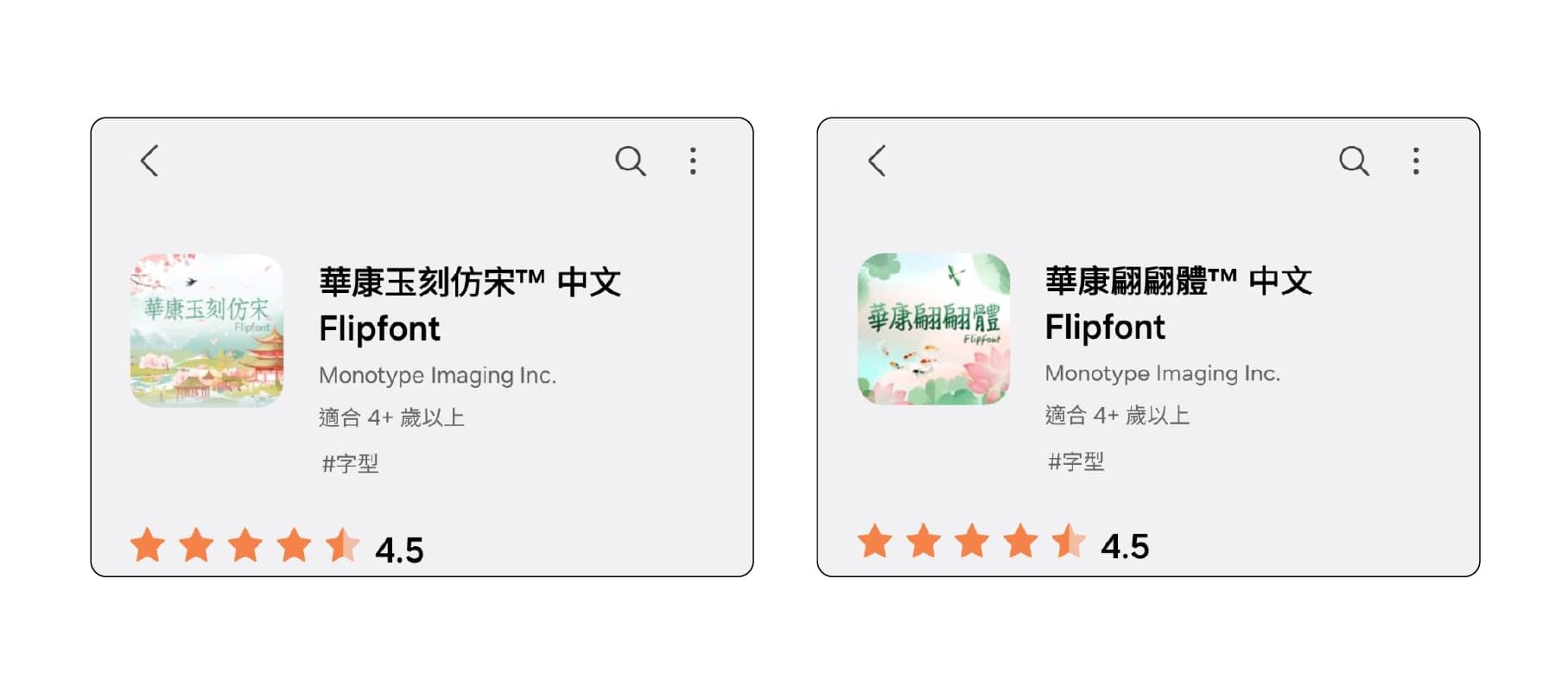
一般來說,用戶無法透過「設定」直接切換字體,最直接的原因是因為Android並未開放相關API讓用戶可以直接註冊系統字體,至於像是Samsung商城這樣的作法,是因為Samsung在開發One UI時,就保留內部接口,可以透過指定方式調用,但僅限於經過認證的廠商。
從Samsung商城安裝的字體,本質上「應用軟體」的形式,只是在一般應用列表中無法看見,本質上是購買了一款應用軟體。
Android APP換字體?
大家可能聽過有部分第三方平台(例如:愛X體、zFxxx)可以做到,通常使用該方法存在許多風險。此類APP大致分為兩種方式達成此目的:
1.使用ROOT
在Android系統啟動時,會自動尋找「etc/fonts.xml」文件,並讀取配置。而ROOT方式就是直接修改該文件,替換字體路徑或是修改字型檔案。
風險顯而易見,首先如果路徑失效,可能會造成系統無法正常啟動,而且只要是一般用戶從市售渠道購買的行動裝置,基本上製造上都不會允許此操作,如果修改過,會導致文件無法通過原廠認證,這可能會失去保固。
加上近期Android開發團隊十分重視安全性,加入了Play Integrity......等相關技術限制,如果發現有對裝置ROOT過,會使許多應用無法開啟。
2.欺敵戰術
ROOT方法太危險?還有許多APP號稱ROOT就可換字體。
此類APP會先安裝「預設字型包」或系統支援字型包,接著讓用戶上傳字體的檔案,次十該應用會將該字體包裝成執行檔案,並且刻意用與「預設字型包」一樣的配置(可能是AndroidManifest.xml),讓系統以為是同樣的東西,調用名稱、家族名、宣告......等都一致,只是最後顯示的圖形不同。
此方法其實也不見會成功,許多廠商已經加入更複雜的較驗系統,包括檢查配置文件的Hash值,防止竄改。
透過APP換字體的風險
上面已經講過ROOT的風險,即便不是用ROOT也可能存在風險,沒有相關技術背景的人使用,APP可能在安裝檔案(多為 apk)嵌入具有風險的程式,會使資訊安全暴露高度風險中。
攻擊手法推層出新,甚至可以夾帶有問題的字型檔案,直接造成系統崩潰或漏洞。例如:CVE-2020-15999的漏洞,透過將與宣告不符合的PNG文件鑲嵌入字體中,造成堆棧溢出(簡單來說,就是騙記憶空間,然後塞入地址,然後程式就會跑到那地址執行惡意程式碼)......等問題。
在極端一點,如果有人刻意將「9」的編碼上,改為「0」的樣式,剛好你掃描了一個付款QRcode,那原本你以為只是支付「1,000」但事實上支付了「1,999」,這就虧大了。
最後,還有許多APP號稱可以換中文字體,但其中字體授權來路不明,品質參差不齊,還可能引發法律問題,千萬勿以身試法!
iOS可以換字體嗎?
可以,但也有限制!iOS與MacOS都可以調用CTFontManagerAPI,可以合法在系統中註冊字體,但僅限於應用中調用。
例如:可以透過文鼎的Fonts Fun安裝字體,並在Word中使用,又或是在iPad中使用剪輯軟體,可調用字體。
應該換字體嗎?
個人手機UI字體,作用域僅限於個人手機,不像對外的設計需要讓大眾存取,確實可以更「自我」的思考這題,假設在安全的情況下,還是可能出現其他的狀況。
狀常見的就是缺字,或品質問題!例如:在Samsung商城啟用〈華康玉刻仿宋〉在下方截圖中就出現,簡體中文無法顯示、西里爾字母字距不自然。
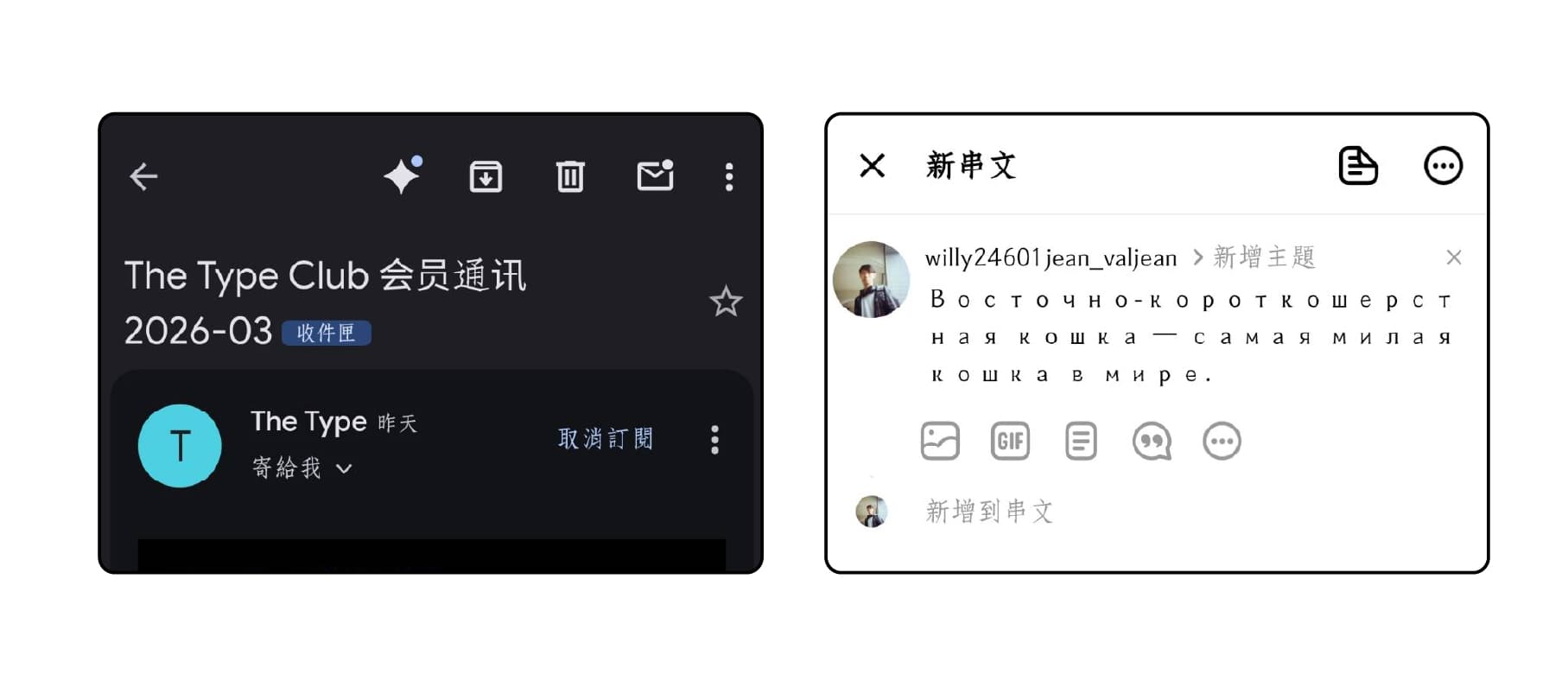
即便顯示正常,我們應該也要思考,在小字號下,這些字體閱讀體驗好嗎?
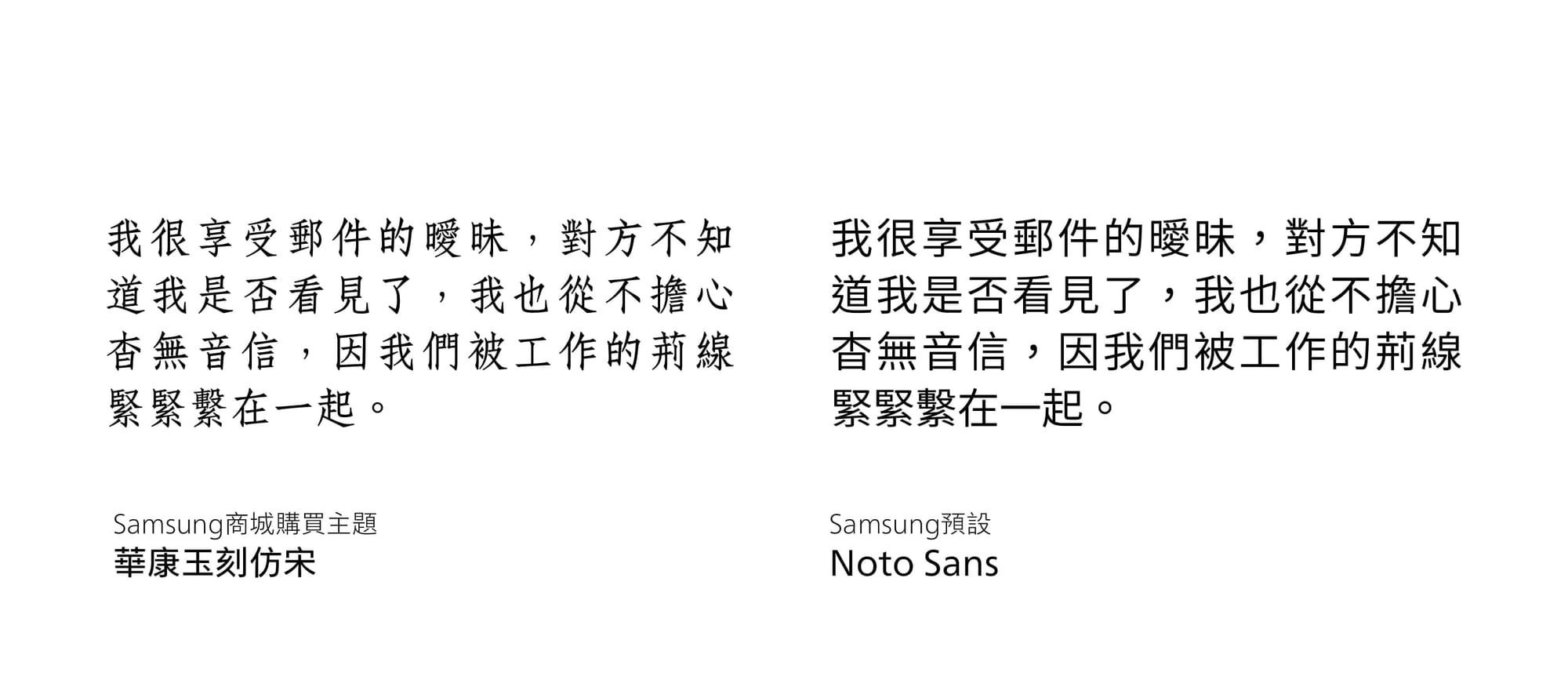
以上舉〈華康玉刻仿宋〉與預設的〈思源黑體〉做為比較,因〈玉刻仿宋〉是目前合法情況下能取得最接近內文字體的設計了,華康官網也是這麼定義他的。感受與評價,留給大家自行判斷。
總結來說,要選擇更換系統UI與否,主要在個人,可以根據自身需要思考,如果自己認為更換系統用字,可帶來幸福感,何嘗不可呢?
唯需在此之前,認知其風險與後果,如想更換,建議依照官方指示方式操作,避免將數位安全暴露於風險之中。